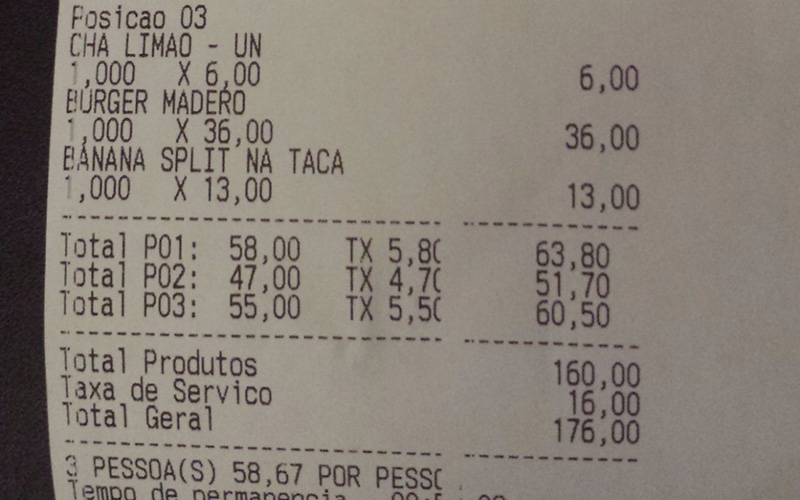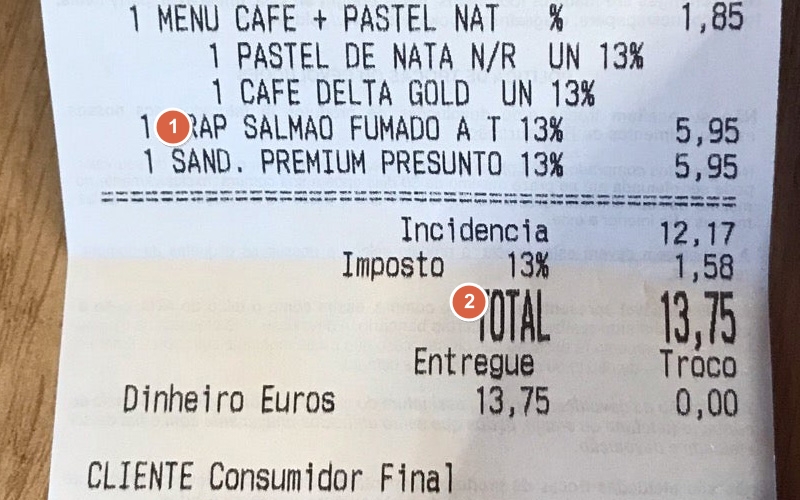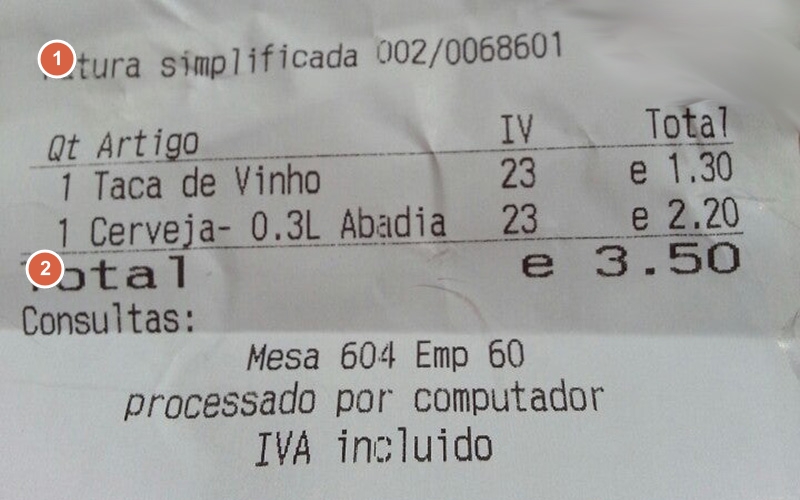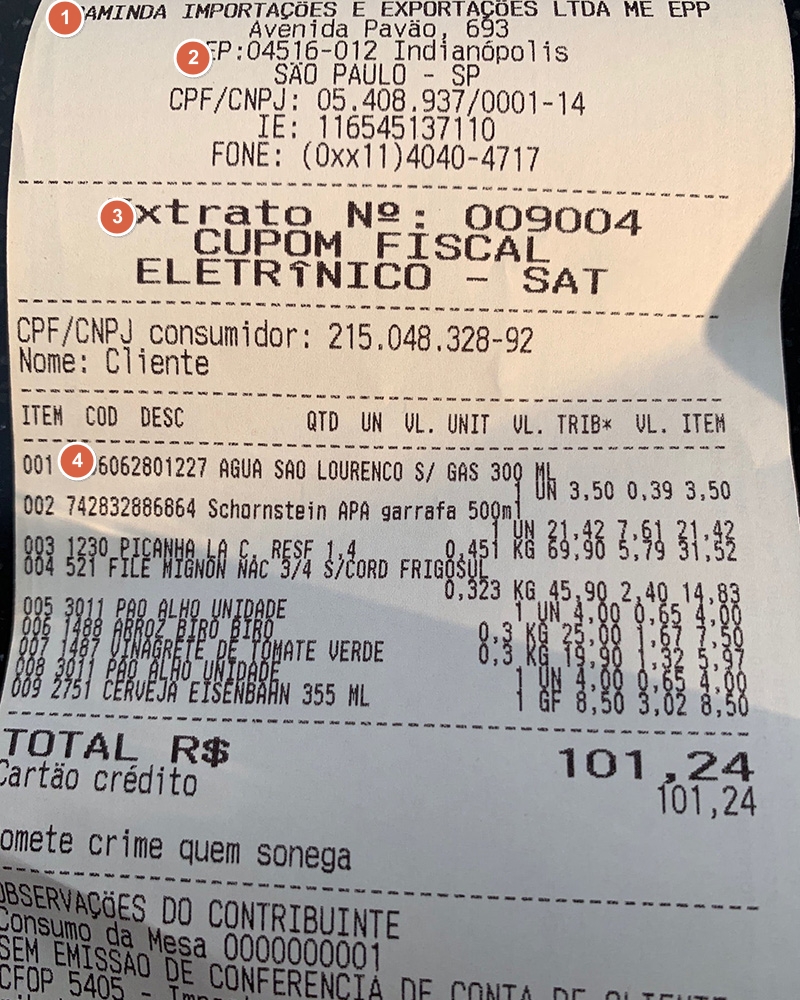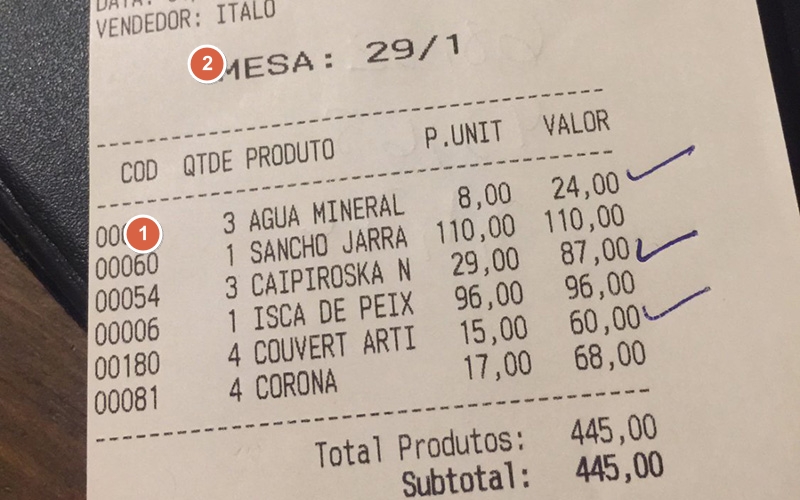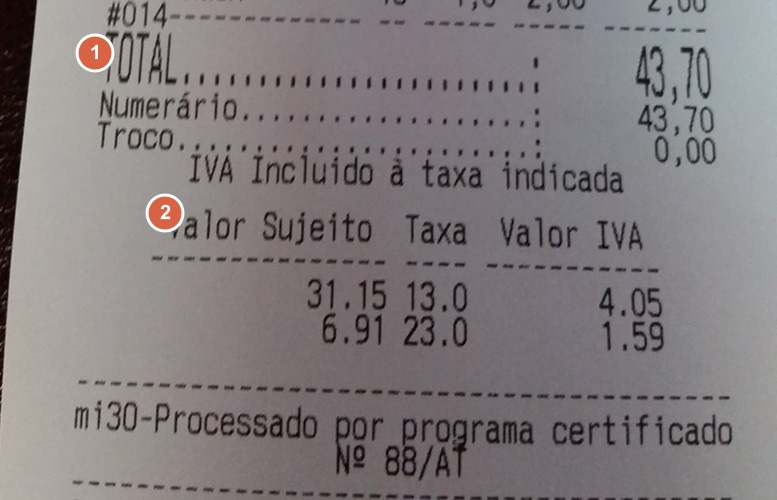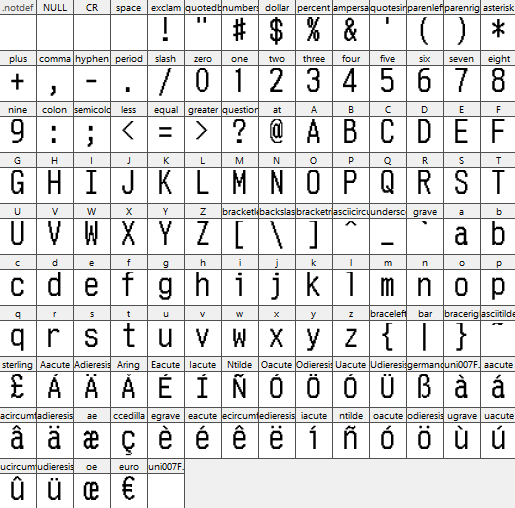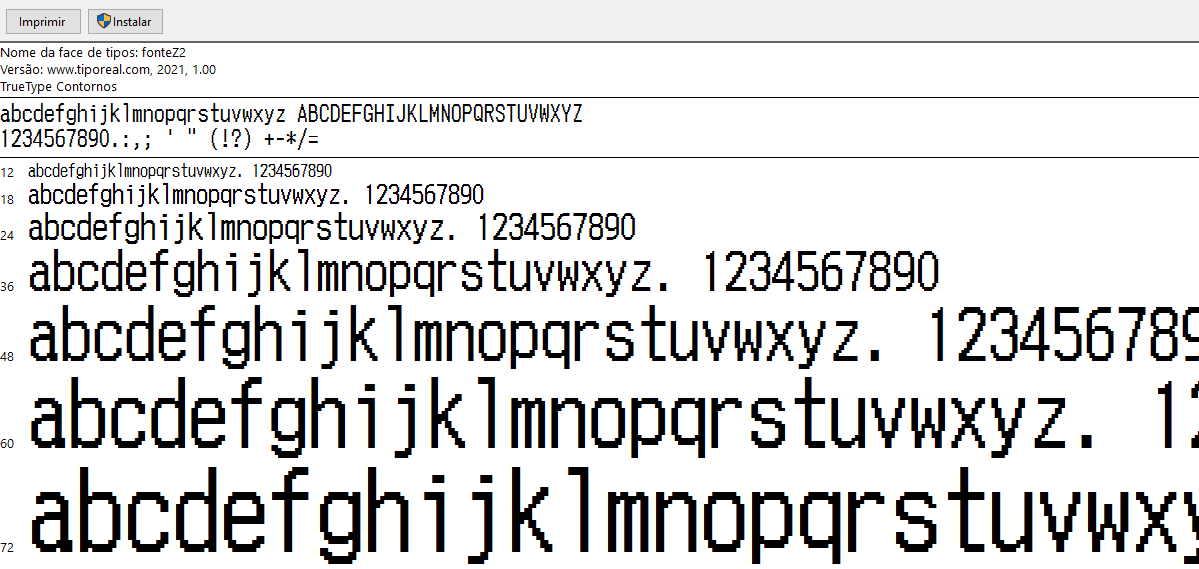
Amostra impressa da fonteZ2⤴
Amostra impressa da fonte para fatura simplificada de um posto de gasolina BP em Portugal⤴
Amostra impressa da fonte para fatura simplificada de um posto combustível em Portugal (❶fonteZ2 ❷fonteZ2-estreito)⤴
Amostra impressa da fonte para fatura simplificada de um restaurante em Portugal (❶fonteZ2 ❷fonteZ2-largo)⤴
Amostra impressa da fonte para cupom fiscal de um restaurante em Brasil (❶fonteZ2-negrito ❷fonteZ2 ❸fonteZ2-largo ❹fonteY2)⤴
Amostra impressa da fonte para nota fiscal de um restaurante em Brasil (❶fonteY2 ❷fonteZ2-negrito ❸fonteZ2)⤴
Amostra impressa da fonte para conta de um restaurante em Brasil (❶fonteZ2-largo ❷fonteZ2)⤴
Amostra impressa da fonte para fatura simplificada de um restaurante em Portugal (❶fonteZ2-estreito ❷fonteZ2)⤴
Todos os personagens⤴
O que parece quando aberto com o visualizador de fontes padrão do Windows⤴